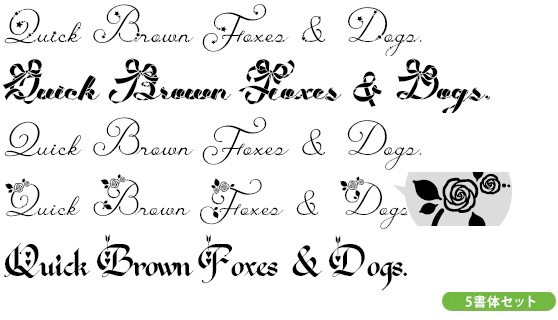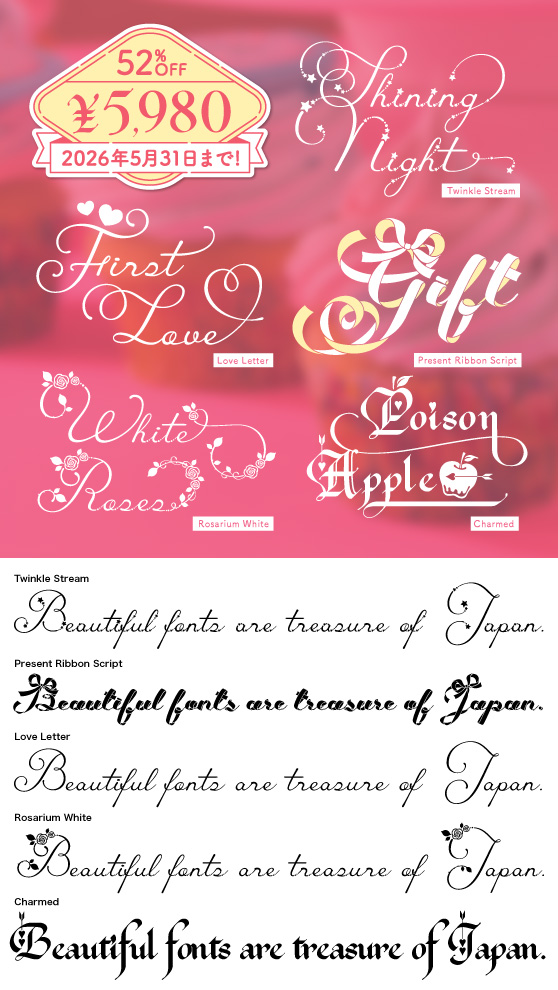
Satsuyako
Satsuyako ビジュ優勝♡オシャレ可愛いフォント集
お洒落で可愛い、異体字も豊富なフォントブランド『satsuyako』の商品の中から、”ビジュ優勝”なデザインに仕上げる5書体を集めた特別セット。
■Twinkle Stream
基本ラテン文字・ラテン文字1補助・ラテン文字拡張A (一部)・ラテン文字拡張B (一部)・結合分音記号 (一部)・約物・記号類 (一部)
[Unicode私用領域に収録]リガチャ (合字)・スタイルセット (01~20)・スワッシュ字形・スモールキャップとその合字・語尾形
■Present Ribbon Script
基本ラテン文字・約物・記号類 ( 一部 )・大文字の異体字ss01~ss05・小文字の異体字ss01~ss08・リガチャ
■Love Letter
基本ラテン文字・ラテン文字1補助・ラテン文字拡張A・ラテン文字拡張B (一部)・結合分音記号 (一部)・記号類(一部)
[Unicode私用領域に収録]リガチャ (合字)・スタイルセット (01~20)・スワッシュ字形・スモールキャップとその合字・語尾形・絵文字、装飾など (数字・[ ] の異体字として収録)
■Rosarium White
基本ラテン文字・ラテン文字1補助・ラテン文字拡張A・ラテン文字拡張B (一部)・結合分音記号 (一部)・記号類 (一部)
[Unicode私用領域に収録]リガチャ (ss01〜09に合字あり)・スタイルセット (大文字01〜08、小文字01〜20)・スワッシュ字形 (大文字5種類、小文字10種類)・スモールキャップ (ss01に合字あり)・語尾形・数字 (ss01に異体字、ss02に絵文字)
■Charmed
基本ラテン文字・ラテン文字1補助・ラテン文字拡張A、B (一部)・結合分音記号 (一部)・記号類 (一部)
[Unicode私用領域に収録]リガチャ (「ff」「fi」「fl」「th」)・スタイルセット (大文字 ss01〜ss11、小文字 ss01〜ss20)・スワッシュ字形 (小文字「ss11」「ss12」「ss13」「ss15」「ss18」)・装飾文字、リンゴの絵文字など
Satsuyakoの紹介
「こんなフォントがあったらいいな」という発想から生まれる、シンプルで少し遊び心のあるフォントが特徴です。筆記体やピクセル風などジャンルは多彩です。カリグラフィーの経験を活かした繊細なデザインと、日本人ならではの感性が織りなす作風は、多くのクリエイターに支持されています。